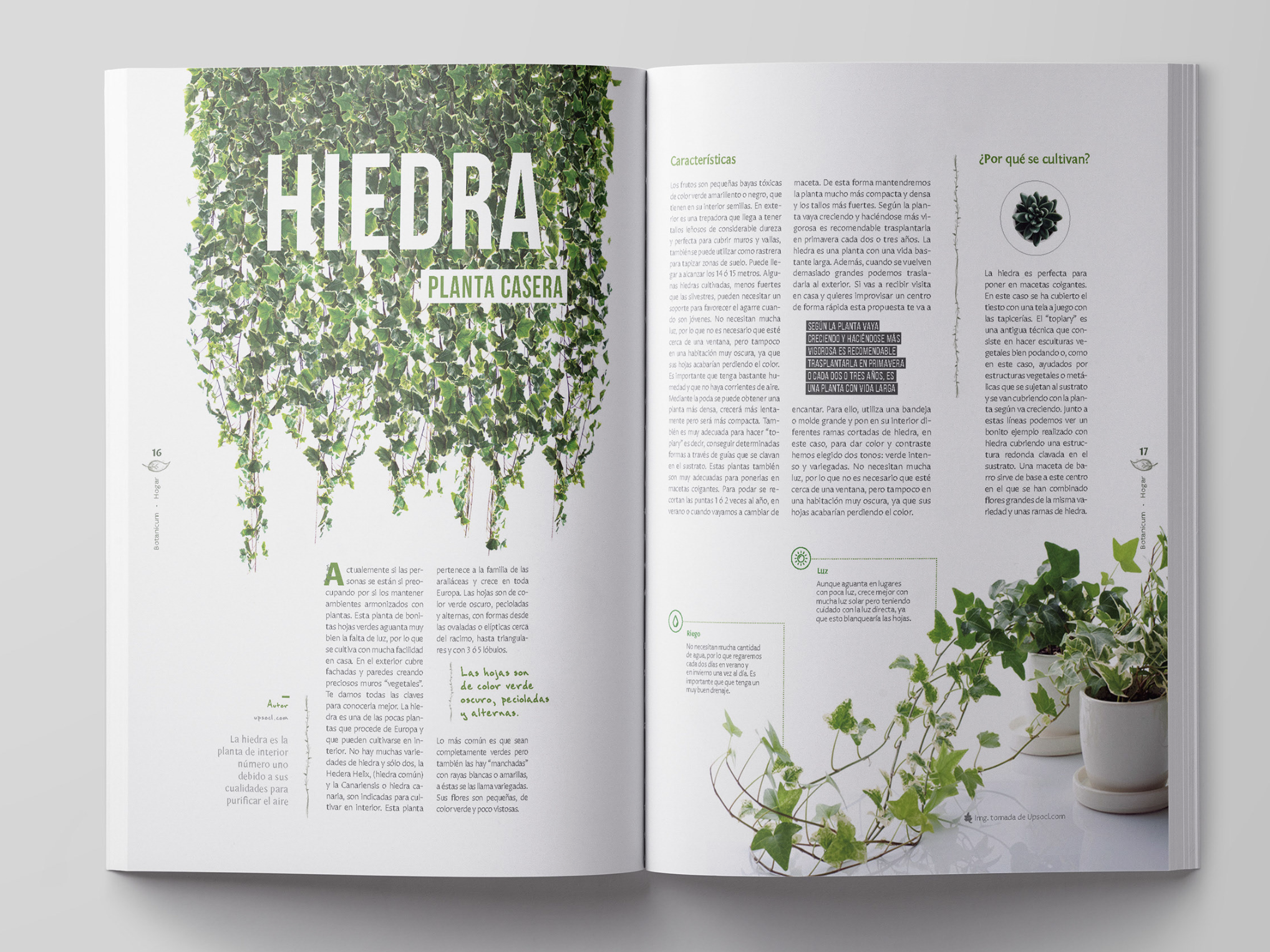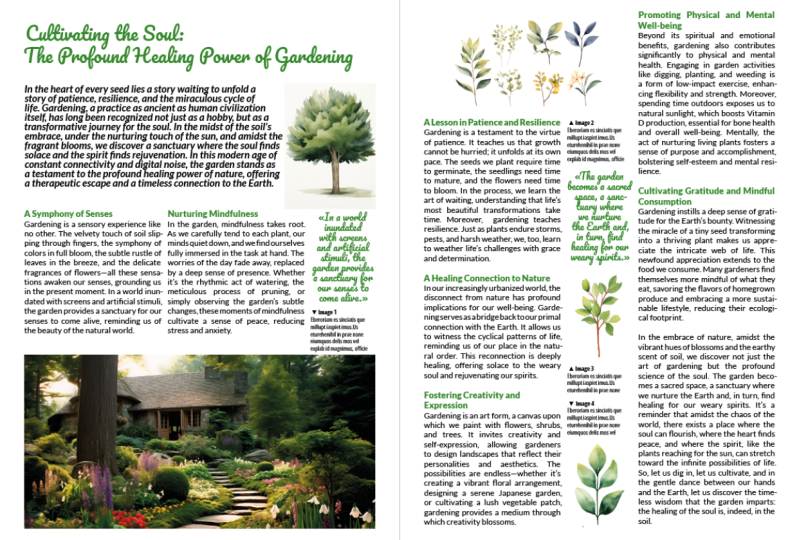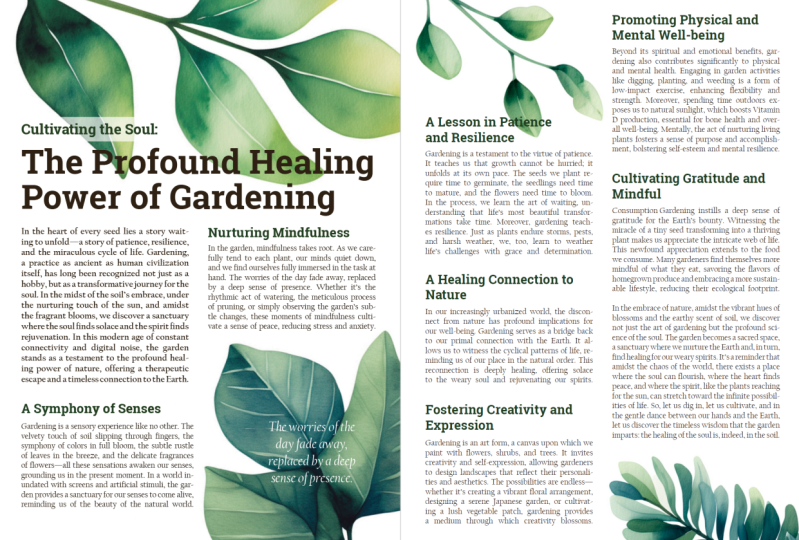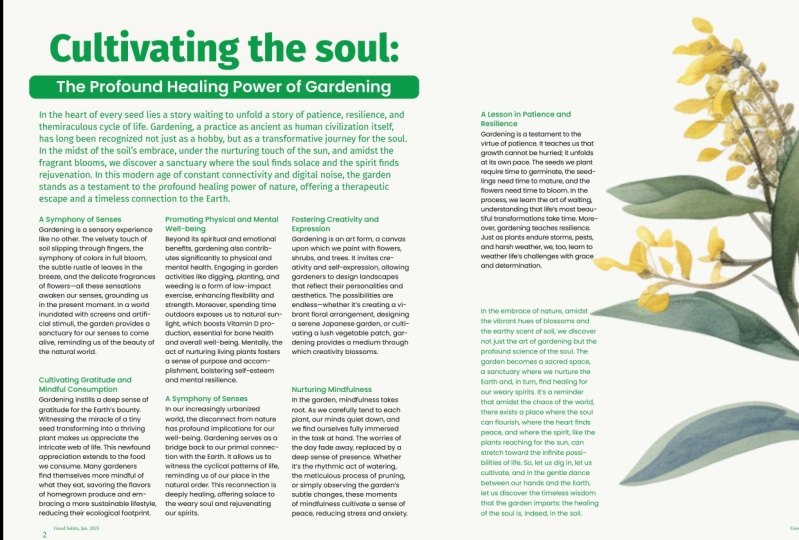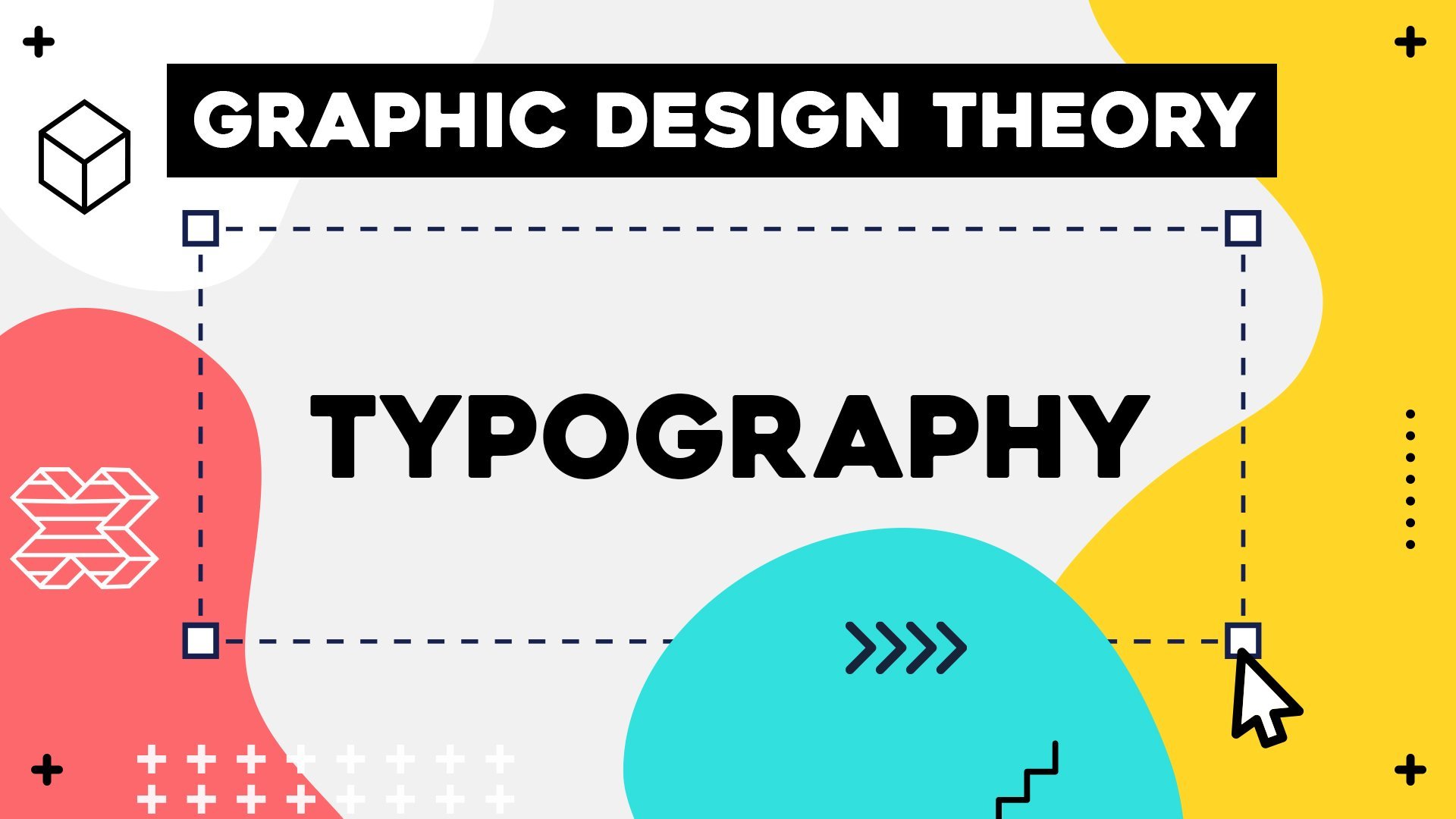
Teoría del diseño gráfico: tipografía
INTRODUCCIÓN
¿Por qué aprender sobre tipo?
Legibilidad
Caligrafía y lettering
Tipo de letra versus fuente
Classificación de tipos de letra
Serif vs Sans Serif
Anatomía de tipografías
Liderazgo, seguimiento, Kerning
Selección de fuentes
Emparejar fuentes
Errores tipográficos comunes
Personalización de fuentes
Texto de interés visual
Jerarquía con fuentes
Consideraciones al elegir color de texto
Alineación de texto
• 20.
Atajos de teclado adicionales
19:34
• 21.
Conclusión
Acerca de esta clase
¡Haz que el texto se vea profesional en todas tus composiciones!
En este curso, exploraremos el ámbito de las fuentes. Aprenderemos los principios críticos sobre cómo usarlos como personaje definitorio de tu diseño, para apoyar y mejorar el mensaje que transmitas.
¿Quién se beneficiaría más de este curso?
Si te gusta la gran tipografía en un cartel, una experiencia de lectura limpia en un sitio web que este curso será un placer para ti desde el principio hasta el final.
Si eres diseñador, lo que dominarás aquí será un elemento fundamental en tu carrera creativa. Comprender las reglas rectoras de la tipografía te permitirá establecer de manera magistral el tono de tu diseño y establecer una jerarquía sutil dentro de la composición para controlar la atención de tus espectadores.
¿Por qué hice este curso?
Hay tantas trampas y errores que puedes cometer, desde una desarmonía visual hasta la interrupción de la legibilidad y la legibilidad del texto en tus composiciones. Creé este programa para que puedas evitarlos intuitivamente y hacer que la tipografía funcione.
Al final de este curso, desarrollarás un ojo crítico para la fuente correcta, verás cómo ajustarla ligeramente para que la buena sea perfecta, y esa diferencia es lo que hace que un diseñador y su trabajo se destaquen.
¿Qué cubriremos en este curso?
Exploraremos todos los aspectos prácticos de la tipografía, incluidos:
• El proceso de selección y emparejamiento efectivos de la tipografía
• Términos clave de anatomía de tipo y la clasificación de tipos de letra
• La diferencia entre tipos de letra y fuentes, caligrafía y lettering
• Alineación de texto, cuadrículas, posicionamiento de texto e imágenes
• Personalización profesional de fuentes
• Mejores prácticas para crear interés visual y controlar la percepción
• Errores comunes de tipografía y formas de evitarlos
• Las reglas doradas para elegir el color del texto
• Atajos de teclado útiles en las aplicaciones de diseño de Adobe
• Y mucho más
Ver todo en acción
A lo largo de este curso, analizaremos varios diseños, desde carteles, portadas de libros, tarjetas de presentación y vallas publicitarias, hasta sitios web, aplicaciones móviles y anuncios de banner. Esto no solo hará que la capacitación sea realmente divertida, sino que también te ayudará a comprender y recordar los términos que cubrimos a través de estos ejemplos,
También repasaremos cuidadosamente cada opción de configuración para ajustar el tipo y explorar cómo afectaría a la visualización y la legibilidad generales.
Sobre mí y mi nueva serie de teorías del diseño gráfico
Esta nueva serie de teorías del diseño gráfico (la tipografía es la segunda parte) es la esencia de mis más de 15 años de enseñanza de diseño gráfico y más de 20 años de trabajo como diseñador gráfico e ilustrador freelance.
Tuve la suerte de enseñar a más de 100 000 estudiantes de todo el mundo y fui votado como uno de los 5 mejores instructores de Adobe del mundo.
1. Introducción: El objetivo principal de la tipografía es la comunicación efectiva. Pero puede lograr mucho más que asegurar la elegibilidad y legibilidad del texto buena tipografía también puede marcar el tono de un diseño, establecer jerarquía dentro de una composición y captar la atención de los espectadores En este curso, cubriremos todos los aspectos de la tipografía, incluido el aprendizaje sobre anatomía de tipos, alineación de textos, clasificación de tipos de letra, errores tipográficos comunes y formas de evitarlos, y mucho más para que la capacitación sea atractiva y ayudarlo a comprender y recordar los términos Analizaremos diversos diseños desde carteles, portadas de libros, tarjetas de presentación y vallas publicitarias, hasta sitios web, aplicaciones móviles y anuncios de banner. Al final de este curso, nunca mirarás los textos de la misma manera. Nuevamente, estarás juzgando la carnicería de nombres de actores en carteles de películas, avisando regs y ríos en revistas, y escudriñando las divertidas opciones en los menús de los restaurantes Si bien esto puede molestar a su familia y amigos, se sentirá mucho más seguro como diseñador gráfico junto con el emocionante proyecto de clase que espero que complete al final del curso También tienes la hoja de trabajo de análisis y el término glosario para ayudarte a practicar todo lo que has aprendido Espero que estés tan emocionado como yo de comenzar y sumergirte en el mar del conocimiento y hermosos ejemplos de diseño gráfico. 2. ¿Por qué aprender sobre Type?: La primera y probablemente la más importante pregunta es, ¿por qué deberías aprender sobre la tipografía en primer lugar Bueno, la mayoría de los diseños tendrían tipo en ellos. Algunos de ellos están confiando en el tipo mucho como una revista, un folleto o un póster. Pero otros diseños que tal vez sean más pesados en ilustración o fotografía, tal vez solo tengan cantidades menores de texto. Pero el tipo sigue siendo generalmente un detalle integral e importante que obviamente ayuda a comunicar el mensaje al que está destinado el diseño. Porque no lo olvides, el diseño gráfico es una forma de comunicación visual. Y además de visuales e imágenes, el mensaje más claro que siempre podemos transmitir usando texto Sin embargo, el texto también es un poco más restrictivo que las imágenes, ya que se basa en el lenguaje que estamos usando y a veces incluso en el tipo de lenguaje que estamos usando Entonces, incluso para un hablante de inglés, podría estar usando términos que no son familiares. Entonces, comparado con las imágenes, el texto puede ser siempre un poco más restrictivo No obstante, puede ser mucho más claro en lo que sea que estés tratando de comunicarte. En mi pantalla, puedes ver ejemplos de todo tipo de diseños diferentes. Aquí tenemos portadas de libros, pósters, empaques de productos, revistas, diseños web, sitios web, banners web, ilustraciones, logotipos, diseño UX, e incluso créditos de películas y letreros de calles. Lo que es común entre todos ellos es el uso de elementos textuales Y no estoy tratando de hacerlo, o ni siquiera siento que necesito convencerte que dominar y trabajar con texto es crucial para cualquier diseñador Porque al igual que otras habilidades como manejar el color, por ejemplo, o idear buenas composiciones, trabajar con texto y comprender la tipografía esencialmente te va a dar confianza cada vez que tengas que crear un diseño La tipografía es un tema enorme y tiene mucha profundidad. Así que podríamos pasar muchas, muchas horas cubriendo todas estas reglas y aprendiendo cada término y definición que se te ocurra. Y no creo que eso sea útil. Entonces lo que creo es que hay ciertos términos y definiciones que tienes que conocer, y estos son muy útiles y realmente te ayudarán a mejorar tu trabajo. Mientras que hay otros que también pueden ser útiles en casos muy específicos o en caso que estés planeando crear o diseñar tus propios fondos. Pero mi objetivo con el discurso es realmente ponerte al día, a un nivel muy fuerte y seguro donde entiendas a lo que debes prestar atención, cómo debes elegir tus fondos, cuáles son las consideraciones, ¿cómo debes emparejarlos? Y realmente enfocarme en estas habilidades cruciales y practicar ejemplos reales es lo que creo que va a ser más útil. Entonces esta no es de ninguna una guía completa que cubre cada término y definición, sino más bien una fuente de conocimiento condensada y simplificada en la que puede confiar siempre que necesite crear cualquier cosa que involucre elementos textuales Entonces ahora que tenemos claro por qué es útil aprender sobre la tipografía, comenzaremos con una diferencia muy importante entre legibilidad y legibilidad en 3. Legibilidad: Probablemente hayas oído hablar de legibilidad o legibilidad, o tal vez de ambas Y es bastante difícil diferenciar estos dos términos u objetivos a los que realmente tienes que prestar atención como diseñador. legibilidad es probablemente la que más escuchaste y la que más probablemente tenga sentido Básicamente significa si puedes leer algo o no. Entonces esto es más sobre si físicamente eres capaz de darle sentido a algún texto en un diseño. Ahora bien, suele haber una clara diferencia entre manejar copia corporal, que tendrías en libros y revistas, y esos son los principales elementos textuales Entonces podrías tener el párrafo de introducción o párrafo de entrada, a veces más grande en tamaño de texto Y entonces tendrías el resto del ejemplar escrito en texto de menor tamaño. Pero entonces también tienes encabezados, títulos o títulos de capítulos, que suelen ser mucho más grandes en tamaño y formateados de manera diferente Entonces, para ser claros, todos estos elementos deberán ser legibles, por lo que el espectador deberá poder leerlos. Pero cómo los presentas realmente depende de su parte que estén jugando dentro del diseño. Si bien el body copy es un texto más largo que tiene que ser fácil de leer, los títulos siempre podrían ser un poco más juguetones porque son más cortos y son de mayor tamaño, así que hay más espacio para jugar con ellos. Entonces, por ejemplo, aquí del lado izquierdo, tenemos un gran número que está marcando el capítulo superpuesto por el título real del capítulo ¿Afecta esto a la elegibilidad? Yo diría que no porque tenemos un claro contraste entre los colores. Entonces tenemos negro y rojo uno encima del otro, muy fáciles de distinguir. Y además tenemos un enorme contraste de tamaño e incluso la fuente utilizada. Entonces, mientras que el texto en negro está usando una fuente sensorial normal como Helvetica, tenemos una fuente de roca condensada utilizada para los números en el fondo para asegurar la elegibilidad En el lado derecho, tenemos el conjunto de colores más estándar y más cómodo utilizado, telón de fondo blanco y texto negro. Si alguna vez usas el texto blanco opuesto sobre fondo negro o texto brillante sobre fondo más oscuro, eso nos referiríamos como texto invertido. Y aún puede funcionar. Sin embargo son los mismos colores, solo están invertidos. El diseño todavía va a sufrir un poco de legibilidad, así que no recomendaría usarlo para conjuntos de textos más largos, como para un libro o una revista Donde para un cartel como este, podría funcionar bastante bien. Y puede destacar fácilmente y también establecer el estado de ánimo o el tono del diseño. Entonces, ¿por qué este póster usaría fondo negro? Bueno, por alguna razón, siempre que pensamos en el jazz, generalmente se toca de noche. Entonces ya tiene esa connotación en nuestra mente, y sobre todo porque el texto también se refiere a esto como un entretenimiento nocturno, realmente tiene sentido Pero tampoco olvides, en el piano, que es el instrumento más utilizado para el jazz, tendrías las teclas en blanco y negro, que por supuesto podrían representarse con fondo blanco y texto negro encima del mismo. No obstante, la mayoría de los pianos, los instrumentos reales que utilizan los músicos de jazz son negros, por lo que tener un fondo negro y mucho espacio negativo establece esa proporción natural del instrumento y el teclado en él Entender todo eso realmente comienza a ayudarnos a apreciar la composición y la elección de colores en este póster. Ahora que empezamos a entender cómo trabajar con legibilidad, aquí hay algunos ejemplos que desafían el concepto de hacer legible el texto Por ejemplo, tenemos este cartel vacío donde todavía podemos leer el título, y todos esos subtítulos son información secundaria, pero está desafiando al espectador. Tenemos que trabajar un poco más duro para armar todo, y casi tenemos que dar la vuelta a la página para poder leer las cosas correctamente. Entonces esta composición o maquetación definitivamente afecta la legibilidad Lo reduce, pero como no hay mucho texto por el que pasar, no va a ser molesto. En cambio, será un poco más de un ejercicio divertido y lúdico para repasar la información del cartel o volante. También puede haber ejemplos y razón por la que un diseñador elegiría meterse con personajes o fuentes como aquí. Por ejemplo, hay muchas formas en las que el espectador tiene el reto de poder leer. El texto principal no sólo se divide en varias líneas, sino que además no hay una alineación clara, por lo que tenemos borde irregular tanto a la izquierda como a la derecha Pero lo que es más importante, tenemos incluso a cada uno de los personajes divididos o divididos en pequeños pedazos. Entonces todos estos están trabajando en contra de la legibilidad. No obstante, también hay cosas que lo están apoyando. El tamaño, en primer lugar, del texto que aquí se utiliza, pero también el contraste del fondo. Por lo que el negro es obviamente el color de mayor contraste utilizado en este diseño. Eso realmente destaca del fondo a pesar de que de nuevo hay algunas formas confusas y coloridas detrás de él. Y esto solo se remonta a la lección principal y más importante para aprender una vez que entiendas cuáles son las reglas en este caso, que necesitas asegurar la legibilidad, el siguiente paso es siempre empezar a empujar esos límites Por lo que entender las reglas te dará la confianza para empujar los límites y realmente desafiar a tus espectadores sin hacer que tus diseños sean molestos o confusos. Eso no quiere decir que siempre tengas que hacer diseños como estos. Nuevamente, tenemos muy baja legibilidad sobre este texto aquí o este en el que tenemos ciertos caracteres realmente estirados. Sin mencionar el tipo de ilustraciones donde el texto realmente no está destinado a ser leído. Se utiliza más como elemento gráfico para recrear una representación o de nuevo, para transmitir cierto mensaje Pero además de usar el texto de estas formas más poco convencionales, mayoría de las veces se quiere conservar realmente la legibilidad Entonces quieres tener una legibilidad muy buena como en el diseño de la interfaz de usuario Tiene que ser muy claro el mensaje, donde los usuarios pueden encontrar ciertas características. Y el texto también tiene que establecer una buena jerarquía, ya sea texto negro sobre fondo o texto invertido. Como hemos visto antes, tú como diseñador tienes que pensar en la legibilidad como un slider que puedes ajustar para ciertos elementos como los nombres de una pizza En este caso, la legibilidad se puede bajar un poco para agregar ese sabor y estilo a los nombres, mientras que los ingredientes y la copia adicional a continuación y sobre todo llaman a la acción Elementos como los botones deberían tener una legibilidad mucho mayor lograda, principalmente en este caso mediante el uso de fuentes que generalmente son mucho más fáciles de leer 4. Legibilidad: Entonces es el momento de hablar ahora de legibilidad, que es la otra forma de pensar sobre cómo debes presentar el tipo en tus diseños Y la principal diferencia aquí en comparación con la legibilidad, es si tu espectador o lector querría leer tus diseños o los elementos textuales dentro de tus Entonces no se trata de poder leerlo, que era legibilidad Se trata de si querrían leerlo o no. Entonces se trata más de su deseo, ya sea que quieran leer tu copia o no, o de cuánta diversión o disfrute obtienen de ella mientras la leen. ¿Cómo se puede mejorar la legibilidad? Puedes pensar en la legibilidad como lo fácil de usar que es tu tipo, o la ergonomía de tu Y la forma más efectiva de mejorar la legibilidad de tus diseños, sobre todo si tienes mucho texto, es tener tantos puntos de entrada como sea posible Hablaremos de esto más adelante, pero esencialmente es para tener estos puntos claros donde los lectores puedan comenzar a leer sobre este spread. Tenemos muchas áreas donde pueden comenzar su lectura. También tenemos un encabezado o título claro aquí. También tenemos otra pequeña sección ahí. También tenemos estos enormes números nos ayudan a saltar a través del texto para que podamos seguir claramente la dirección o ruta original pretendida de la copia Y todos estos punteros y divisiones en el ejemplar nos ayudan a digerir la información y pasar por ella sin demasiado esfuerzo Y el hecho de que el orden del texto aquí esté un poco por todas partes, así que esté saltando entre las páginas no es un problema tan grande porque en realidad ayuda a mover el ojo del espectador del lado izquierdo a la derecha y luego volver de nuevo. Por lo que casi da un poco de ejercicio o reto sin, de nuevo, ser molesto. Y ese también es un buen equilibrio con el que tienes que jugar como diseñador. Así que no quieres que tu diseño sea demasiado aburrido y que tenga muchos textos en un solo lugar. Pero tampoco quieres que tus diseños sean demasiado desafiantes de leer. Entonces aquí hay un ejemplo interesante. Tenemos muchos textos en este bloque en el centro. Esa es nuestra copia corporal, pero tenemos un punto de entrada que es un drop cap. Y también tenemos algunos códigos de sondeo que están rompiendo el texto. Y luego el título principal y el párrafo introductorio aquí en el centro Como se trata de un periódico, podemos esperar mucho ejemplar que necesita ser colocado en una sola página. Y a pesar de que tenemos este gran bloque de texto con seis columnas, sigue siendo bastante divertido gracias a esa ilustración que se divide por el texto y está apareciendo en la parte superior e inferior. Y también por tener estos espacios negativos o pausas dentro del diseño Eso de nuevo, solo ayuda a crear un poco de alegría y dejar algo de respiro para el lector Pero también hay otro detalle interesante aquí. El título de la revista es en realidad casi por completo, o al menos la mitad, está oculto detrás de la ilustración. Ahora bien, esto también es algo que comúnmente se ve en las portadas de revistas también. Y se basa en que el lector está familiarizado con el periódico y reconocería el título aunque no esté completo. Nuevamente, aquí, esto en realidad está bloqueando la legibilidad. Simplemente somos físicamente incapaces de leer esa parte del texto. Pero en términos de legibilidad, esto está marcando un reto divertido y nuevamente, puede atraer la atención del lector porque aquí deja un espacio en blanco, que nuestra mente tendrá que rellenar a través de este título En términos de legibilidad es realmente débil en términos de legibilidad En realidad es bastante bueno porque despierta el interés del lector Y por último, te voy a mostrar tres ejemplos donde tanto la legibilidad como la legibilidad son malas, y tengo que advertirte, podría lastimarte los ojos Aquí están estos ejemplos. Primero, tenemos señalización que se utiliza para los autobuses de Londres. Ya no creo que este letrero esté fuera. Seguro que ha sido arreglado por transporte para Londres. Pero cuando fue fotografiada, claramente tenía algunos problemas, tanto afectando la legibilidad como la legibilidad El mayor problema es el mal rastreo o kerning, que provocó que estos personajes acercaran demasiado entre sí en ciertos lugares, casi convirtiendo algunos de estos en ligaduras Sin querer, las ligaduras son pares de fuentes que normalmente son caracteres individuales dentro de una Pero también tenemos muy mala separación de detalles importantes como el Stop M dividido en dos líneas, o London Bridge, nuevamente, dividido en dos. Que incluso con una pequeña medida o ancho de línea como aquí, aún deben mantenerse juntos en la misma línea. Ahora lo que es aún peor es que creo que incluso hay un error gramatical Entonces este apóstrofe, creo, es un error porque se suponía que decía raíces 43.141 pero actualmente significaría que estos números pertenecen a gramaticales o errores tipográficos como este afectarían principalmente a la legibilidad porque causa confusión y el lector podría malinterpretar alguna información en caso de que una señal que se trate de llegar de un lugar a otro puede ser un problema bastante caso de que una señal que se trate de llegar de lugar a otro puede ser un Los otros dos ejemplos que tenemos aquí son igualmente malos en términos de legibilidad y legibilidad también Tenemos muy malas elecciones de diseño en cuanto a qué colores se usan uno encima del otro, qué tipo de fuentes se utilizan para cierta información, El kerning y el seguimiento y alineación de las cosas, la variedad innecesaria de fuentes apiladas en un solo Y podría continuar, estoy seguro de que puedes ver todos estos. Y creo que para que todos puedan mejorar, es igual de importante mirar estos malos ejemplos y analizarlos como pasar tiempo y mirar buenos ejemplos que hemos visto anteriormente en este video. Entonces ahora que estás al tanto de tus principales objetivos, mejorando la legibilidad y legibilidad, continuación hablaremos un poco sobre los términos básicos de la tipografía 5. Caligrafía y letras: Probablemente hayas oído hablar de la caligrafía o las letras a mano, y estas son habilidades completamente diferentes al tipo de configuración Como diseñador gráfico, estás trabajando principalmente con caras tipo. Entonces estos son teléfonos que puedes usar para tus diseños y todos los personajes ya están ahí. Sólo hay que empezar a escribirlos y obviamente trabajar en la composición. Compare con esto, si se le pide que haga caligrafía o letras a mano, eso es más una forma de arte similar a la ilustración donde cada personaje tiene que ser dibujado individualmente en un cierto estilo, es difícil distinguir claramente estos dos términos No obstante, yo diría que la caligrafía es más un enfoque tradicional, y aquí se pueden ver algunos ejemplos en varios idiomas Los verías en enciclopedias y léxicos antiguos. Tradicionalmente, este tipo de escritura se usaba para todo, incluidos los títulos, las mayúsculas e incluso el body copy. Sin embargo, hoy en día en la caligrafía moderna, se suele utilizar para palabras o frases individuales Y la copia corporal rara vez se escribe en este estilo. Incluso los personajes individuales pueden verse muy complejos y agradables, por lo que pueden usarse fácilmente como elemento de diseño en una revista, por ejemplo, o como un gorro realmente destacado por otro lado, las letras a mano, que pueden ser tradicionales o digitales hoy en día Obviamente en el ipad, es muy fácil usar el lápiz de manzana, por ejemplo, y poder crear este tipo de composiciones. La forma en que puedes diferenciar esto la mayor parte del tiempo de caligrafía es que aquí el texto se usa más de composición, por lo que cada una de las palabras formará un layout más grande y crea una bonita insignia, mayor parte del tiempo en una forma Puede ser un círculo, un cuadrado o cualquier forma orgánica. Y es muy común tener también algunos elementos florales, decorativos, o detalles ilustrativos combinados con las letras Como dije antes, la caligrafía y las letras a mano no son una habilidad que se te requerirá para poder hacer como diseñador gráfico Esta es una forma de arte completamente independiente y más similar a la ilustración como mencioné antes. No obstante, si estás interesado en producir trabajos como este, los principios y teorías que estamos aprendiendo en este curso te serán sumamente útiles. 6. Tipo de letra vs fuente: Probablemente ya estés familiarizado con el término fuente. Y la mayoría de los diseñadores gráficos usan esto mucho, solo refiriéndose a qué fuente usar en un diseño específico. O qué fuentes se pueden emparejar bien juntas. No obstante, tipografía es otro término que deberías estar familiarizado Y en realidad se puede argumentar que la forma correcta de referirse a la mayoría de las fuentes es en realidad llamarlas tipografías Por ejemplo, Helvetica es una cara tipo. Futura o Gotham son también otros dos tipos de caras. Las fuentes son las diferentes variaciones de las mismas. Normalmente llamamos a un tipo face una familia de fuentes Helvetica. El tipo face tendría, por ejemplo, una versión de fuente ultra ligera o la fuente Helvetica Roman, o la fuente Helvetica Y todas estas variaciones o fuentes conforman la familia de fuentes, o tipo face llamado Helvetica Nadie te va a corregir si estás diciendo que Helvetica es una fuente Pero si quieres ser más preciso, trata de referirte a ella como una cara tipo. Pero claro, todavía se puede decir, por ejemplo, yo usé la fuente Helvetica board para el título en un diseño En otra lección, hablaremos más sobre lo que entra en una tipografía o cuáles son los contenidos generalmente de una tipografía también Cuáles son las caras tipo con las que se recomienda acostumbrarse a trabajar y las que realmente te servirán bien, principalmente gracias a la variedad de fuentes dentro de ellas. 7. Clasificación de tipos de letra: Lo más probable es que ya hayas oído hablar de Serif y San Serif tipografian fondos y esa es una forma de clasificarlos Pero en realidad hay bastante más que eso. Y también es importante saber cuándo usar qué clase de tipo cara. Entonces en esto contigo, estaremos cubriendo la información más importante sobre este tema. En primer lugar, ¿qué son las serifs? Estos son los pequeños detalles o adornos que ayudan a que las letras sean más distintivas en las tipografías serif, mientras que sol en mientras que sol Entonces en este caso, sin serifs, tipo de tipografías no tendrían ninguno de esos tipos de adornos Serían mucho más simplistas y minimalistas. Fuente Serif, a veces también referida como romana. Y eso se debe principalmente a que se basaba en el estilo de grabado de la escritura romana, mientras que a veces se hace referencia a Sunserif como Sin embargo, eso es sólo un cierto tipo de sanserif. Probablemente sea mejor no usar ese término como clasificación general antes de aprender más sobre la diferencia entre los tipos de letra sanserif y serif Aquí hay un poco de información de antecedentes sobre los tipos de letra de historia o evolución Y este es un tema enorme y no me gustaría cubrir todo. Pero esta infografía realmente resume bien las cosas, porque muestra muy claramente los cuatro tipos principales de clases o categorías para fuentes o tipos Entonces primero tenemos guión dentro del cual el más común que reconocerías son las letras negras. Entonces estas son las letras realmente antiguas y tradicionales inventadas alrededor de la época en que comenzó la impresión por primera vez. Así que en realidad es alrededor de la época Johannes Gutenberg inventó el tipo móvil con la imprenta Y este tipo de caras siempre estaban emulando letras a mano También evolucionaron a lo largo del tiempo, por lo que se volvieron un poco más fáciles de leer con el nuevo formato casual y luego con la versión formal de ellos. Pero como puedes ver, fueron los primeros que consideraríamos como tipos de letra Y entonces no mucho después, aparecieron las primeras fuentes serif, o tipografías Entonces este es el segundo color que tenemos aquí, y hay muchas categorías para ellos, pero el primero que consideraríamos aparecer alrededor de principios del siglo XVI fue la categoría de estilo antiguo La prenda de Adobe es una instancia de ella. Pero claro, hay muchas variaciones y ha evolucionado y cambiado a lo largo del tiempo. Pero incluso viendo este texto aquí, todavía se puede decir esa herencia y sensación clásica que se ha conservado incluso en este nuevo formato digital. Entonces volviendo a nuestra infografía, podemos ver que los fondos de Servir realmente existieron por más de 500 años, pero Sunsifunds solo aparecieron alrededor de 1.800 Ahora esta es nuevamente una transición importante en la historia de las caras tipo y la más notable e importante a mencionar es Caslon, que está aquí podemos ver a William Caslon que está aquí podemos Cuarto fue el que introducía el tipo de impresión Sunserif. Este fue un cambio revolucionario o paso en el grabado y realmente afectó la forma que trabajamos con el tipo hasta el día de hoy Pero ahora sabes que a pesar las caras tipo Sunserif se ven modernas, en realidad ya tienen más de 200 años Y también evolucionaron y cambiaron a lo largo del tiempo, igual que las caras tipo Sunserif Entonces hay varias categorías como grotesca, humanista, geométrica, cuadrada, y así sucesivamente, así sucesivamente Por último, la última categoría que consideraríamos fuentes decorativas apareció a principios del siglo XX. Y puedes encontrar abundancia de estos en sitios de fuentes gratuitas como Dafot Pero incluso en las fuentes de Adobe, varias etiquetas te llevarían a este tipo de fuentes decorativas, como divertidas, por ejemplo, o funky Ahora bien estos, por supuesto, tienden a ser los menos legibles de todas las clases. Sin embargo, pueden ser geniales para capturar un tono de voz o tema muy específico para tu copia. Y por supuesto, estos se utilizan principalmente para títulos y titulares y no para la copia corporal o mayor cantidad de texto. 8. Serif vs Sans Serif: Entonces, ahora que tenemos una breve comprensión de cómo evolucionan estas clases de tipos de letra, podemos concentrarnos en la diferencia entre Serif y Porque como diseñador gráfico, estos son los más importantes con los que estarás trabajando. Y debes conocer las ventajas y desventajas de usar una sobre la otra. Como guía general, mayoría de los creativos recomendarían trabajar con tipografías Serif o Roman en forma impresa y usar Sunserif en la web Esto es un poco de generalización. Pero es cierto que los atributos o detalles de Serif ayudan con la legibilidad, porque antes que nada, dan una guía general o dirección horizontal a la lectura Todos estos pequeños detalles tienden a guiarte a través de la lectura del texto. Pero lo que es más importante, también pegan personajes y forman mejores unidades para las palabras. Nuevamente, para mayor cantidad de texto, eso es muy útil, porque los espacios entre las palabras serán más distintos. Y como dije, las palabras se pegarán formando mejores unidades. Entonces, ¿por qué usaríamos Sunsif si es más fácil leer los tipos de letra Serif Bueno, una de las mayores razones por las que en el diseño digital usarías Sunserif sobre Serif debido a la pixelación en los detalles de Serif la pixelación en los detalles Ya tienes texto pequeño, digamos para tu body copy y está en un sitio web, en esos textos pequeños, las serifs aún más pequeñas las serifs aún más definitivamente comenzarían a pixelarse Y eso no es realmente ideal que te gustaría usar, especialmente para copias más pequeñas Sunserif cuando se trata de sitios web y aplicaciones, interfaz de usuario, así sucesivamente Con base en algunos estudios, alrededor del 70% del texto en la B está usando fuentes Sunserif Ahora no significa que no puedas usar Sunserif en forma impresa o Serif en Estos son más como lineamientos generales y consideraciones útiles. Pero mientras entiendas el razonamiento detrás de esto, podrás romper con él en ciertos casos. Y claro, también puedes emparejar estos dos para que no tengas que ceñirte a usar una clase en un diseño en particular. Puedes tener tu copia de intro y tu título o encabezado en fondo Sanserif, pero puedes tener la copia del cuerpo Otro ejemplo de combinar tres tipos diferentes de categorías. Tenemos el encabezado establecido en un texto sanserif condensado. Tenemos estos grandes números y el título principal ambientado en más de un fondo decorativo. Y entonces tenemos la copia del cuerpo o la mayor cantidad de texto, e incluso esta llamada aquí puesta en Serif En general, siempre que estés usando fondos Seri, ayuda a mantener tu diseño un poco más moderno, fresco y simplista En comparación con el uso de fondos Serif, tendrías un toque clásico un poco más tradicional en tus diseños Y aquí hay otro ejemplo, solo usando el fondo Seri en la portada de un libro Tanto para este diseño gráfico aquí en el centro, pero todo el resto del texto se establece en Serif Los rasgos o diferencias entre las dos clases de fondos son claramente visibles en el logotipo de Google, por ejemplo. Entonces, cuando se actualizó para usar Sun Serif de la fuente original Seri, ya marcó una gran diferencia en la percepción de la marca y el propio motor de búsqueda Es interesante ver cuánta diferencia hace, ya sea que uses una clase de texto u otra. Pero también solo quería señalar que con Google Logo, una característica distinta que mantuvieron es esa inclinación o rotación en la E, lo que la hace, de nuevo, un poco más única Pero también otra cosa menos obvia es que cambiaron los colores. Probablemente el más destacado es el verde. Cómo se volvió más brillante, pero todos los demás colores cambiaron apenas muy ligeramente. Pero volviendo a las diferencias o pros y contras entre estas dos clases principales de caras tipo, también vale la pena mencionar que fuentes serif suelen funcionar mejor a la hora de poner las cosas en cursiva Esto es algo que se puede ver claramente demostrado aquí. Itálico o cursiva también se conoce a veces como oblicuos Estos son los caracteres ligeramente inclinados, mientras que las fuentes sunserif tienden a tener oblicuos de bajo contraste, lo que significa que no son tan diferentes de los Tendrías mucho más contraste para cursiva cuando se trata de las caras de tipo serif Entonces puedes ver que este texto aquí se ve muy diferente y contrastando con el conjunto de caracteres regular. Esto vuelve a ser una gran ventaja cuando se trata de libros donde a cursivas u oblicuos menudo se usan cursivas u oblicuos para resaltar ciertas cosas Digamos que alguien está hablando o se puede establecer algo a lo que se refiere en este formato. Cuando trabajas con fuentes san Serif, tendrías que confiar más en los diferentes pesos Así que puedes usar versiones ligeras o negrita, o ultra negrita para resaltar ciertas partes del texto. Aquí hay otro ejemplo interesante que muestra que cuando estás usando la fuente Serif, siempre es más fácil distinguir caracteres en comparación con San Serif porque como la O y la C para este tipo en particular es indistinguible cuando solo estás mirando la parte superior de la Mientras que el Serif en la C, ese pequeño detalle adicional siempre revelará lo que estás viendo, incluso cuando solo estás revisando la parte superior Entonces esto es obviamente una ventaja y nuevamente, ayuda a distinguir a los personajes. No obstante, agregar más detalles en general en el diseño gráfico significa que las cosas se vuelven más complejas. Y es por ello que los sunserf ons suelen considerarse más casuales, Y en realidad los niños prefieren o encuentran mucho más fácil leer el texto sunserif Entonces hay muchas consideraciones, pros y contras. Y no quiero animarte a que solo uses una clase de caras tipo sobre la otra. Se trata de familiarizarse con las propiedades. Y una vez que empieces a trabajar con ellos, desarrollarás una intuición sobre cuándo cierta clase es mejor que otra Y si eres nuevo en el diseño gráfico y sigues luchando por diferenciar lo que es Serif o cara tipo Sunsif, entonces te recomendaría jugar a este juego Le disparé al Serif donde puedes configurar tu nivel. Y digamos que ahora somos de peso medio, así que sólo voy a elegir eso. Conseguiremos dos personajes y siempre hay que filmar a los Serif Ahora conseguimos cuatro de ellos, así que sólo tenemos que hacerlo de nuevo. Y conseguimos más y más. Y entonces tenemos que ser lo más rápidos posible pasando por esto. Y podemos ver que tenemos una cierta cantidad de errores permitidos, seis en este caso. Y hasta el momento tenemos tanto puntaje y encontramos 14 fuentes serif correctas Recomiendo encarecidamente este para jugar. Pero también hay otro bueno, tipo War.com donde de nuevo, tendrás que poder decir qué tipo de cara estás mirando Esto te ayudará a familiarizarte con las caras tipo más utilizadas. También es una buena práctica comenzar a recordar si una cara tipo tiene serifs o no En este caso, estamos diciendo Times New Roman. Entonces seguimos adelante. Cuando ahora veamos de nuevo Times New Roman, siempre verás si tienes razón o no. En el lado izquierdo, podrás decir la respuesta correcta para la pregunta anterior. Ahora estamos mirando, creo, Helvética Este es óptimo, este es Dido, y estamos en racha Ahora solo intentemos seguir así, Dido otra vez, y este también es Dido. Y voy a parar ahí porque final voy a cometer un error. Recuerden, hasta la tipografía es un tema enorme y hay mucha historia y reglas Aunque ahora mismo te sientas un poco intimidado por todas estas cosas diferentes que cubrimos, recuerda, todo se reduce a lo mucho que disfrutas haciendo las cosas y consideras mecanografiar caras a tus amigos Una vez que los conozcas y como trabajar con ellos, será mucho más divertido y estarás disfrutando del proceso de diseño 9. Anatomía de tipografías: Cuando se trata de términos y definiciones, lo más aterrador que puedes encontrar es la anatomía del tipo Hay tantos nombres para ciertas características dentro de caracteres o letras, y puedes ver algunos de estos aquí en este tablón de notas de Miller. Pero no voy a aburrirte con todo esto. Y créeme, no es necesario conocer todos estos para ser buenos en el diseño gráfico. Sin embargo, hay algunos términos específicos que me parecieron muy útiles para mi trabajo profesional. Y realmente mejoró la forma en que trabajo con el tipo. Creo que lo primero y más importante que hay que recordar son las líneas distintas dentro del texto. Entonces comenzarías con la línea de base. Ese es probablemente el más importante. Ahí es donde estarían sentados la mayoría de tus personajes. Ahora por supuesto, algunos detalles cruzarían esta línea y se llamarían descendentes para caracteres en minúscula, pero también pueden ser colas en caracteres en mayúsculas Y para la mayoría de las caras tipo, en realidad tendrías una línea específica llamada línea descendente, a la que se alinearán todos estos detalles de descenso Esto es muy importante cuando tienes múltiples líneas una encima de la otra porque la guía o el espaciamiento entre tus líneas tendrán que establecerse de manera que estos detalles no choquen ni se acerquen demasiado a los otros detalles en la parte superior llamados ascendentes Y nuevamente, para estos detalles tendrías la línea ascender, que como puedes ver, normalmente es ligeramente superior a la altura de la tapa, que se utiliza para la parte superior de los caracteres mayúsculas Ahora incluso ahí, hay una ligera diferencia. Normalmente los personajes redondos como el O tendrían un poco de rebasamiento, por lo que pasarían un poco por encima de la altura de la tapa La razón principal de esto es que si se mantuvieron en el mismo tamaño, la altura de la tapa sería la misma para los caracteres Q o C. De hecho, se sentirían más pequeños para personajes como E, y eso se debe principalmente ese gran espacio o espacio negativo dentro de ellos, que también llamamos espacio de contador o bola, si queremos ser técnicamente precisos en términos de la anatomía de tipo. Así que recuerda el término x altura, esto es en realidad algo de lo que hablaremos más adelante. Esto se utiliza para el tamaño o la altura de los caracteres en minúscula. Y la altura de la tapa, que se utiliza para la altura de caracteres en mayúscula. Y también hay una medida llamada altura del cuerpo, que serían las líneas superior e inferior, que nunca serían superadas por ninguno de los personajes. Y ese suele ser el espacio mínimo que necesitarías para tu interlineado o interlineado para mantener el texto legible. Ahora además de las alturas, el ancho de para los caracteres también son importantes. Y la mayoría de las fuentes o tipos de letra son proporcionales, es decir, que los caracteres tienen un ancho diferente a ellos, lo que llamaríamos ancho de cuerpo Así lo podemos ver en el carácter x aquí. Pero volvería a ser diferente para los caracteres en mayúscula. E incluso entre caracteres, eso sería una diferencia bastante grande, el ancho de W o siempre sería muy diferente del carácter I. Por ejemplo, escribe caras donde tienes el ancho del cuerpo y el ancho de carácter para todos los caracteres igual, nos referimos como monoespacio Esto es en realidad algo que se inventó para máquinas de escribir, por lo que es muy raro que usáramos texto monoespacial en formato digital, porque la mayoría de los tipos de letra son ahora proporcionales aparte de algunas excepciones como Pero lo más importante, lo que debes recordar es que puedes tener la misma altura para los caracteres, pero el ancho establecido o el ancho del cuerpo pueden ser muy diferentes entre tipos de letra o fuentes con las que estás trabajando ¿Por qué es importante? Bueno, principalmente porque si estás eligiendo un tipo de cara de fondo que tenga un ancho amplio establecido de ancho de cuerpo para los caracteres, entonces será más difícil ajustar la misma cantidad de texto en una página en comparación con si estás usando una fase de tipo de ancho de conjunto más estrecho A veces la diferencia puede ser extrema. Por lo que puede tener el doble de texto establecido con el mismo tamaño de texto pero diferente ancho de conjunto en una página. Aquí hay un ejemplo más sutil, pero aún así algo que muestra la diferencia entre dos fondos establecidos en el mismo tamaño. Pero debido a que los atributos de los fondos tienen diferencia tanto para el sitio como para el ancho del cuerpo, produce un espacio bastante diferente que el texto va a ocupar. Una vez más, el tamaño de fuente es el mismo, pero el libro de Century School ocupa mucho más espacio en comparación con Times New Roman. De nuevo se trata del acto de equilibrio entre tener más texto condensado y poder comprimir más información en un cierto espacio en comparación con darle a tu texto un poco más de espacio para respirar y hacer que la experiencia de lectura sea un poco más fácil Y a veces incluso haciendo que el texto sea más legible. Ahora, la ligadura es otro término que vale la pena recordar. Esto significa cuando se tienen ciertos pares de caracteres que se pueden representar con un carácter individual. Lo que mejora la legibilidad. Para que puedas ver la diferencia en la parte superior sin usar ligaduras Y para este tipo particular de cara que tiene un conjunto de ligaduras, inmediatamente se vuelve mucho más fácil leer estos caminos específicos una vez que las ligaduras están en uso Además de mejorar la legibilidad, también son buenos reducir el ancho de estos conjuntos de caracteres. E incluso una cosa pequeña como simplemente tener ligaduras disponibles y habilitadas para la copia del cuerpo puede hacer realmente una gran diferencia en términos de la cantidad de texto que puede caber en una página Entonces, al elegir un tipo de letra para la copia del cuerpo, siempre se recomienda verificar si las ligaduras están incluidas o no en ese conjunto de caracteres Como mencioné, además los términos que cubrimos en este video, hay mucho más que puedes conocer y la mayoría de estos pueden ser útiles. Pero créeme, sin conocer todos estos términos que tenemos aquí en la pantalla, aún podrás diseñar grandes cosas y poder trabajar con el tipo profesionalmente. Sin embargo, si quieres estudiarlos, hay muchos recursos en línea. Y también puedes usar este Mill and Note board donde tengo un par de buenas explicaciones y gráficos de información en todos los términos que puedas conocer. Pero también te recomiendo, de nuevo, son dos juegos en Love Typography.com puedes encontrar varios juegos de anatomía de fuentes donde tendrás que pasar por estas Entonces, por ejemplo, con línea de base, habrá que recordar cuál era esa. Entonces creo que ya lo cubrimos y lo más probable es que lo recuerdes. Pero entonces obtendrás también estos otros que no hemos cubierto. El remitente otra vez, es algo de lo que hablamos y así sucesivamente y así sucesivamente. Pero también está este juego llamado Shape Type, donde tendrás que terminar realmente la curvatura de ciertos personajes. Y realmente te ayudará a apreciar esos pequeños detalles y curvas que se utilizan en los personajes. Por cierto, puedes mantener la tecla mayúsculas aquí, para mantener tus anclas, o líneas de dirección rectas, lo cual es la mayor parte del tiempo, importante para estos personajes Y luego cuando sientas que está listo, puedes compararlo con el original. Podemos ver lo cerca que me acerqué, 84% no tan mal. Podemos ver la carta original y luego la mía. Sí. Bueno, ahí no hay tanta diferencia. Vamos a ir al siguiente. Sólo hagamos una más. Bien, entonces tenemos ahora la fuente Si, bastante común, una que se usa a menudo, solo tenemos que arrastrar esto hacia arriba y luego el otro ancla tiene que bajar. Bien, siento que es algo así. Tratemos de configurar esto aquí también. Bien, Este es un poco complicado, 100% seguro. Obviamente, no podemos moverlo de izquierda a derecha, en este caso solo de arriba a abajo. Tiene que ser más suave, estas curvas seguro. Simplemente arrástralo arriba y abajo hasta que obtenga un mejor resultado. Bien, creo que eso está bastante cerca. Vamos a revisar. Bien, así que en realidad lo hemos hecho un poco mejor en esto. Una vez más, original y nuestra carta. Así que asegúrate de darle una oportunidad a estos juegos también si ya estás cansado de aprender los términos que cubrimos. Pero en el siguiente video, por fin vamos a pasar a una pregunta muy importante, Cómo elegir un fondo. 10. Liderazgo, seguimiento, Kerning: Hay tres términos y dos atajos de teclado que aprenderemos en esto contigo. Estos son muy importantes y algo que estarías usando todo el tiempo en tus diseños. Es kerning, líder y seguimiento. Ahora comencemos con liderar porque siento que es el más fácil de entender. interlineado es esencialmente el espaciado entre las líneas en su copia. Esto aplica principalmente si tienes mayor cantidad de texto. Al igual que aquí tenemos algunos párrafos y puestos en dos columnas. Entonces si utilizo el atajo cuando tengo texto seleccionado Alt u opción flecha arriba y abajo. Con esto, puedo ajustar el interlineado para poder espaciar más el texto o tenerlo más comprimido. Ahora bien, si aumentamos el liderato, podemos ver que se vuelve un poco más fácil y más conveniente leer el texto. No obstante, si lo aumentas demasiado, empieza a desmoronarse. Y será más difícil diferenciar dónde termina un párrafo y dónde comienza otro, en comparación con un Ledding más ajustado que teníamos originalmente Así se ve, más espaciado. Ahora claro, no hay que confiar únicamente en el atajo. También puedes llegar a los controles de formato de caracteres y encontrarás el líder aquí justo debajo del tamaño del texto. Esta es la segunda opción más importante con la que tendrás que trabajar. Tiene una función automática que siempre establecerá el Ledding basado en el tamaño del texto Por ejemplo, si establecemos el tamaño del texto en diez puntos, entonces veremos que el Ledding se establecerá en 12 puntos Ese 20% adicional en términos del tamaño del Ledding en comparación con el tamaño de fuente es un valor por defecto que se usa la mayor parte del tiempo para Ledding Pero como hemos visto, siempre podemos anular esto y configurarlo a lo que preferimos. Generalmente, si necesitas comprimir texto en un espacio más pequeño, tendrás que usar un interlineado inferior. Mientras que si tienes más espacio para trabajar, puedes comenzar a aumentar el ledding. Con eso, generalmente, puedes mejorar la legibilidad o hacer que sea más conveniente o cómodo leer tu copia Ahora digamos que quieres ceñirte al uso un tamaño de fuente específico e inicial, pero no tienes suficiente espacio para caber el texto. Acabo de hacer mi marco de texto más pequeño. Y aquí tenemos algún texto sobreajustado. Si presiono comando control I en el teclado. En, en diseño podremos ver exactamente cuánto texto está sobrepuesto Son sólo un par de palabras, pero aún así no tenemos espacio para ello actualmente. Entonces, ¿cómo podemos arreglar esto? Bueno, antes que nada, podemos seleccionar la copia de cuerpo entero. Y luego presione el comando Y solo para volver a nuestra ventana principal y aún así tener el mismo texto seleccionado. Esta es una técnica útil por cierto, siempre que se haya sobreajustado el texto y quiera asegurarse de que también esté seleccionado antes realizar cambios en el formato Entonces ahora que tenemos todo esto seleccionado, en lugar de cambiar el tamaño de fuente o el inicial, usaremos otra opción de alteración de atajo, flecha izquierda y derecha, para ajustar el seguimiento. Ahora, el rastreo es el espacio horizontal o espaciado entre los personajes, que comenzará a condensarlos y los mantendrá más cerca entre sí sin distorsionar por supuesto, a los propios personajes reales Entonces, si voy extremo en esto, eventualmente será casi ilegible y muy difícil ver qué está pasando Pero claro que podemos encontrar ese equilibrio correcto donde casi logramos encajar el texto en el marco de texto. Y aún así tenemos una legibilidad bastante buena en nuestro ejemplar. ¿Dónde puedes encontrar el seguimiento en la configuración? Esta es otra opción que encontrarás bajo los controles de formato de caracteres. Entonces este es el que está aquí. Actualmente fuimos a -40 Si lo puse de nuevo a cero, ese era el rastreo original. Si quiero saltar a un valor específico, digamos -35 también puedo simplemente teclearlo y se puede ver en realidad que ya encaja porque el atajo saltaría automáticamente incrementos de diez puntos Para el seguimiento, podría ser mejor refinarlo y afinarlo usando un valor específico en la barra de control. Ahora bien, qué tan lejos puedes empujar el seguimiento ya sea de una manera menos o positiva realmente depende de la fase de tipo seleccionada. Por lo que varía mucho. Algunas fases tipo como esta son bastante flexibles, mientras que otras podrían ser menos receptivas a este tipo de cambios. Por lo que cubrimos los préstamos y el seguimiento. Pero, ¿qué es el kerning entonces? Esto es muy similar al rastreo. Sin embargo, esto es cuando ajusta de manera individual y única el espaciado caracteres entre ciertos caracteres en lugar de ajustar globalmente e igualmente el espaciado para una mayor cantidad de texto como lo hemos hecho antes. Entonces, por ejemplo aquí con nuestro encabezado, tal vez necesitemos usar un poco de kerning, porque hay un par de personajes como W y A. que parece que tiene un poco de espacio demasiado Entonces, si acercamos el zoom, probablemente puedas ver esto mejor si pongo mi cursor ahí y uso la vieja flecha izquierda y derecha. Es el mismo atajo que rastrear. Pero en este caso, debido a que tenemos el cursor justo jugar específicamente ahí, no va a cambiar a los demás personajes. Se trata de ajustar de manera única este espaciado aquí. Con eso, podría mejorar ya un poco cómo se va a leer este titular, pero también podemos hacer un poco de ajuste entre ciertos personajes como H e I o H y E, donde tenemos estas líneas verticales una al lado de la otra. También podemos ajustarlo un poco. Y luego vamos a movernos un poco más aquí. Siento que yo y puedo ir más cerca y también, y entonces lo más probable es que podamos tener un poco menos espaciado aquí entre estos personajes también. Ahora bien, si nos alejamos, es posible que no notes una gran diferencia aquí. Pero si saltamos de un lado a otro entre el antes y el después, notará que en realidad ajustamos una buena cantidad de espaciado y resultó en un espacio ligeramente más estrecho necesario para el titular Así que en realidad se alinea mucho más agradable con nuestra copia corporal, pero también muy importante, la separación entre las palabras se hizo Porque ahora no tenemos tanto espacio entre las letras individuales. Ning puede mejorar tanto la legibilidad como la legibilidad. Pero lo que es más importante, estos detalles más grandes como titulares, títulos de capítulos o títulos una vez curados, se verán mucho más profesionales que sin el kerning Y no hay ciencia exacta de lo que es el kerning correcto Se trata más de establecer estéticamente un equilibrio o ritmo entre tus personajes. Y si quieres practicar esto y queremos desarrollar un ojo para ello, nuevamente, recomiendo otro juego llamado Current Type, donde podrás arrastrar a estos personajes y luego encontrar el kerning correcto El primer y último personaje, no podrás moverte. Eso establece los límites, pero cualquier cosa intermedia tendrás que jugar con él. Y cuando sientas que terminaste, puedes volver a revisar tu puntaje. Y he hecho un mal trabajo aquí, así que es sólo el 78% de cada 100. Pero probemos con otro. Tenemos fuente Germont o tipografía de la que hablamos antes. Una vez más, intentamos encontrar el kerning correcto aquí. Bien, digamos algo así. De nuevo, estoy bastante mal, así podemos ver solo la solución y mi espaciado. Me muevo la Y demasiado cerca de la. Y en realidad el mejor kerning es dejar un poco más de espacio aquí, no apretar la Y debajo de la barra de la Vamos a otro. Voy a tratar de no acercar demasiado la V a la Y. Algo así. Bien, en realidad lo conseguí perfectamente. Sin embargo siento que todavía hay una diferencia entre la solución y la mía, pero creo que la aceptó como puntaje del 100%. Incluso puedes usar atajos de teclado para este juego, que puedes encontrar aquí en la parte superior. Estos no son los mismos atajos que vas a usar en, en diseño, Photoshop o Illustrator. Pero definitivamente hace que jugar a este juego sea un poco más fácil y más similar a cómo trabajarías profesionalmente con el tipo en estas aplicaciones. En pocas palabras, para su copia corporal o mayor cantidad de texto, siempre preste atención a liderar y rastrear Y utilízalos para mejorar la legibilidad, pero también para poder ajustar la cantidad de espacio que ocupa tu texto Kerning es algo a lo que hay que prestar atención cuando se trata copias más grandes como encabezados y títulos, que tiene menos cantidad de personajes Pero que el espaciado entre los caracteres se vuelve aún más importante y más notorio si no están equilibrados o no distribuidos uniformemente. En el siguiente video, te mostraré cinco de las escenas tipográficas más comunes y cómo eliminarlas en tus diseños 11. Elegir fuentes: En este video, cubriremos un par de mejores prácticas para seleccionar la fuente adecuada para tus diseños. Y yo comenzaría con el dicho que siempre tengo en cuenta las mejores opciones de fuente son las que el lector no nota como fuente, simplemente puede concentrarse en el mensaje. Así que al igual que todo en diseño, menos suele ser más. Así que no exageres las cosas y no escojas una fuente que sea demasiado decorativa o demasiado overs estilizada para cierto mensaje Como aquí, elegí una fuente que me pareció que va un poco con esa sensación de guerra sin ser demasiado militarista. Entonces, si quisiéramos, fácilmente podríamos reemplazar esto por algo más que conecte con el ejército o la guerra. Si buscábamos tal vez algo así como stencil, éste está aún más enfatizado Y podemos hacer esto más grande, solo para que podamos ver esos detalles ahí. Y siempre es un buen equilibrio decidir qué es demasiado y qué sigue estando bien usar. Como en este caso, yo diría que también puedes salirte con la tuya fácilmente y podría funcionar. Pero realmente depende de qué tipo de publicación sea esta, el público objetivo. Entonces hay que conocer mejor a sus lectores y con qué se relacionarían mejor. Ahora tengo que ser honesto contigo, casi todos los diseñadores, cuando inician una e incluso después de años de diseñar, probablemente pierdan más tiempo en seleccionar fondos en Adobe Applications. Entonces déjame demostrarte esto. Digamos que no estoy seguro de lo que quiero usar para el rubro en este caso, y solo iría aquí al selector de fondos. Entonces esta es la parte más peligrosa de la aplicación donde simplemente seguiríamos desplazándonos hacia arriba y hacia abajo y buscando fondos Ahora bien, si eres un poco más avanzado, podrías usar las flechas arriba y abajo y las atraviesas mucho más rápido y encuentres quizás las potenciales de esa manera. Y si eres bueno, incluso podrías empezar a configurar los que más te gusten como favoritos, lo que puedes hacer de nuevo aquí desde el menú desplegable. Y luego solo puedes poner la pequeña estrella en las que elegiste o que seleccionaste. Y de esa manera más adelante podrás filtrar muy rápi